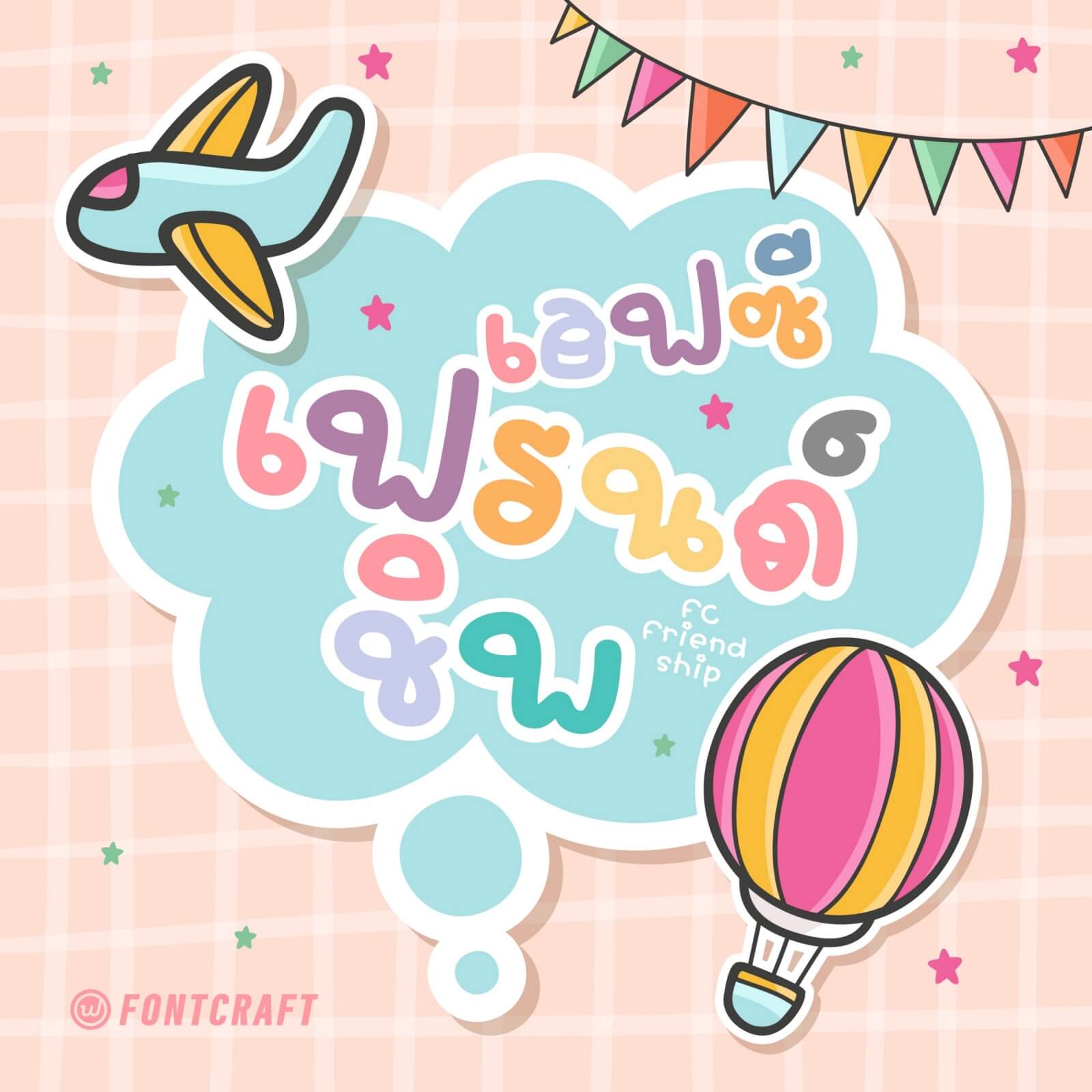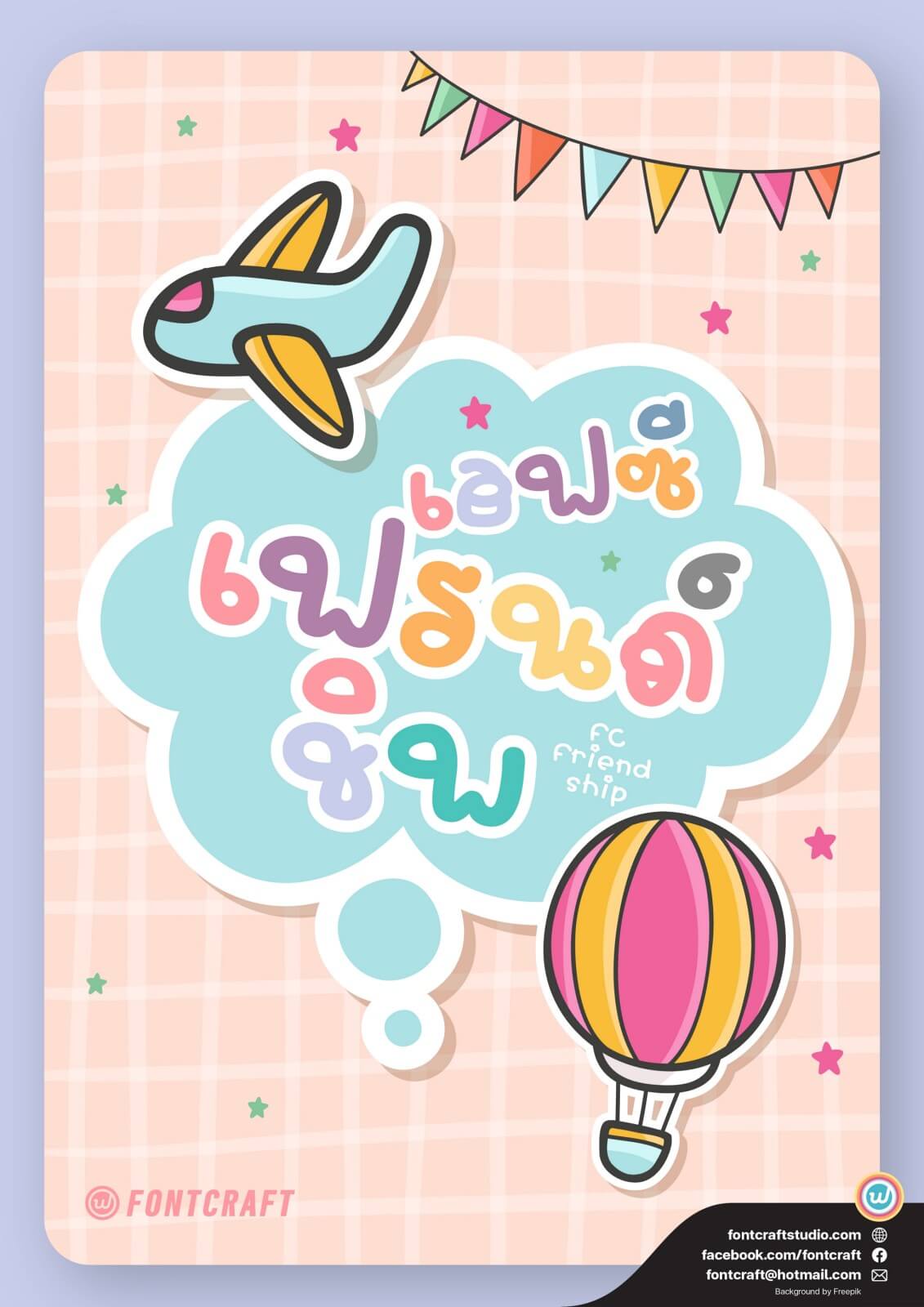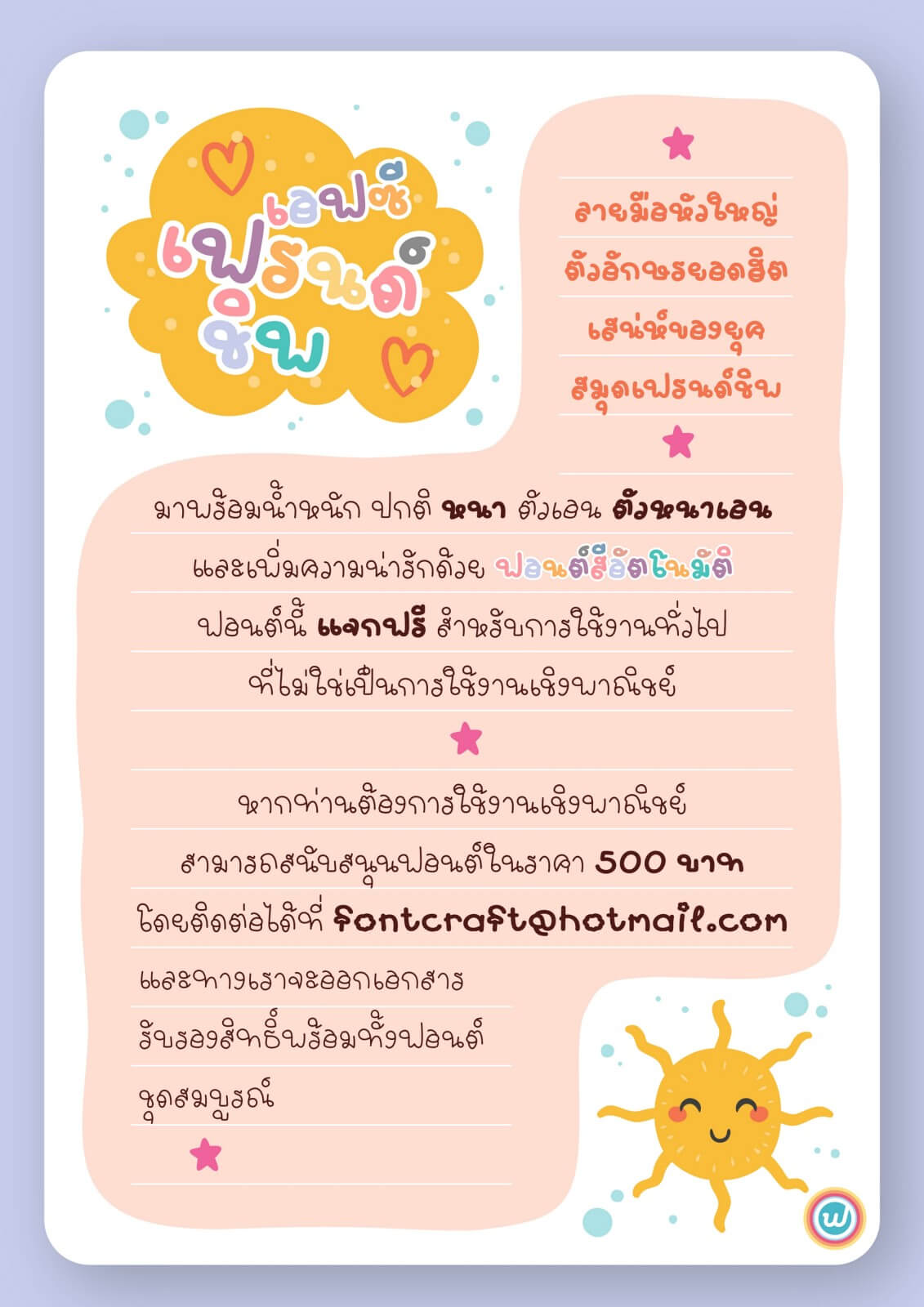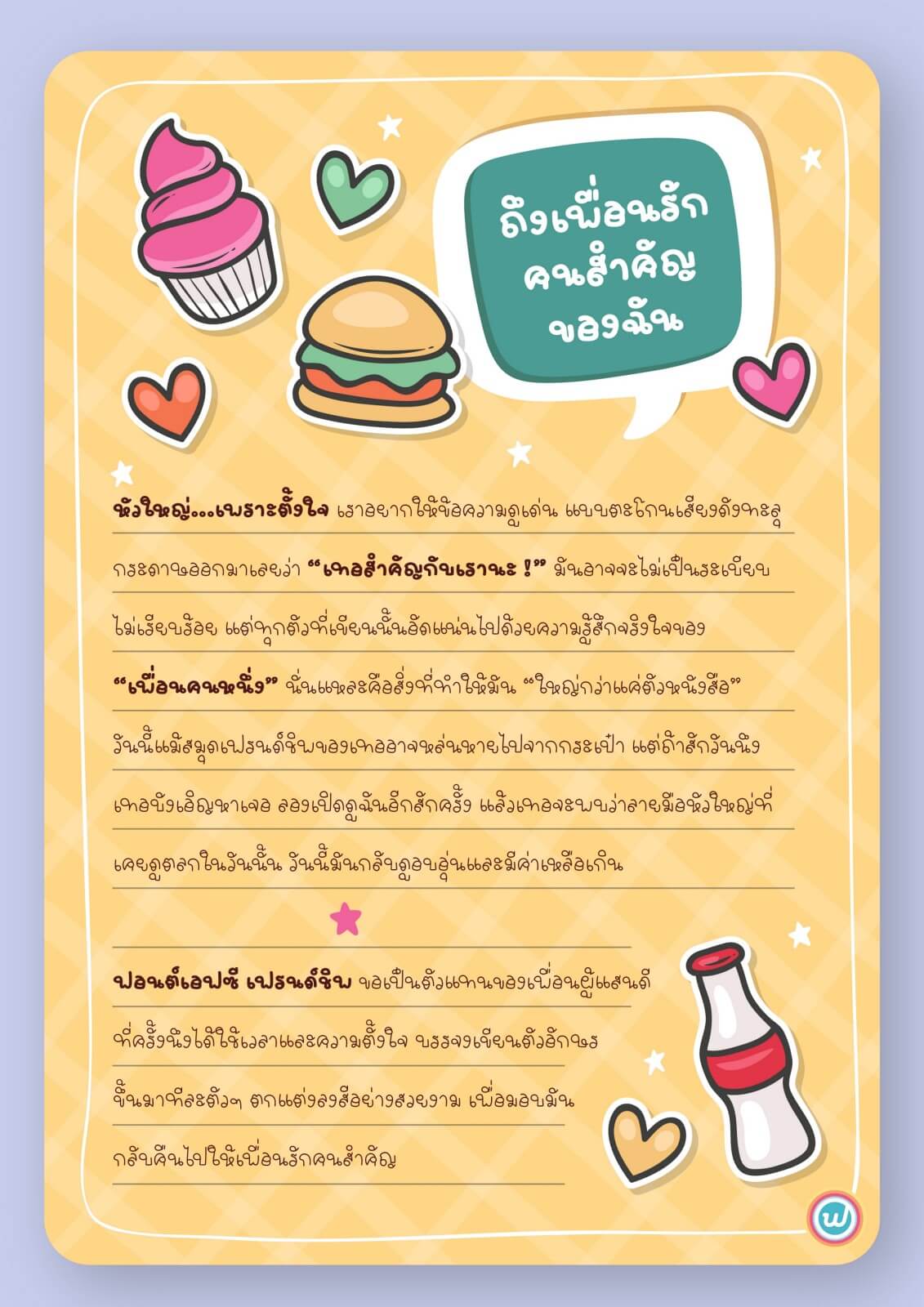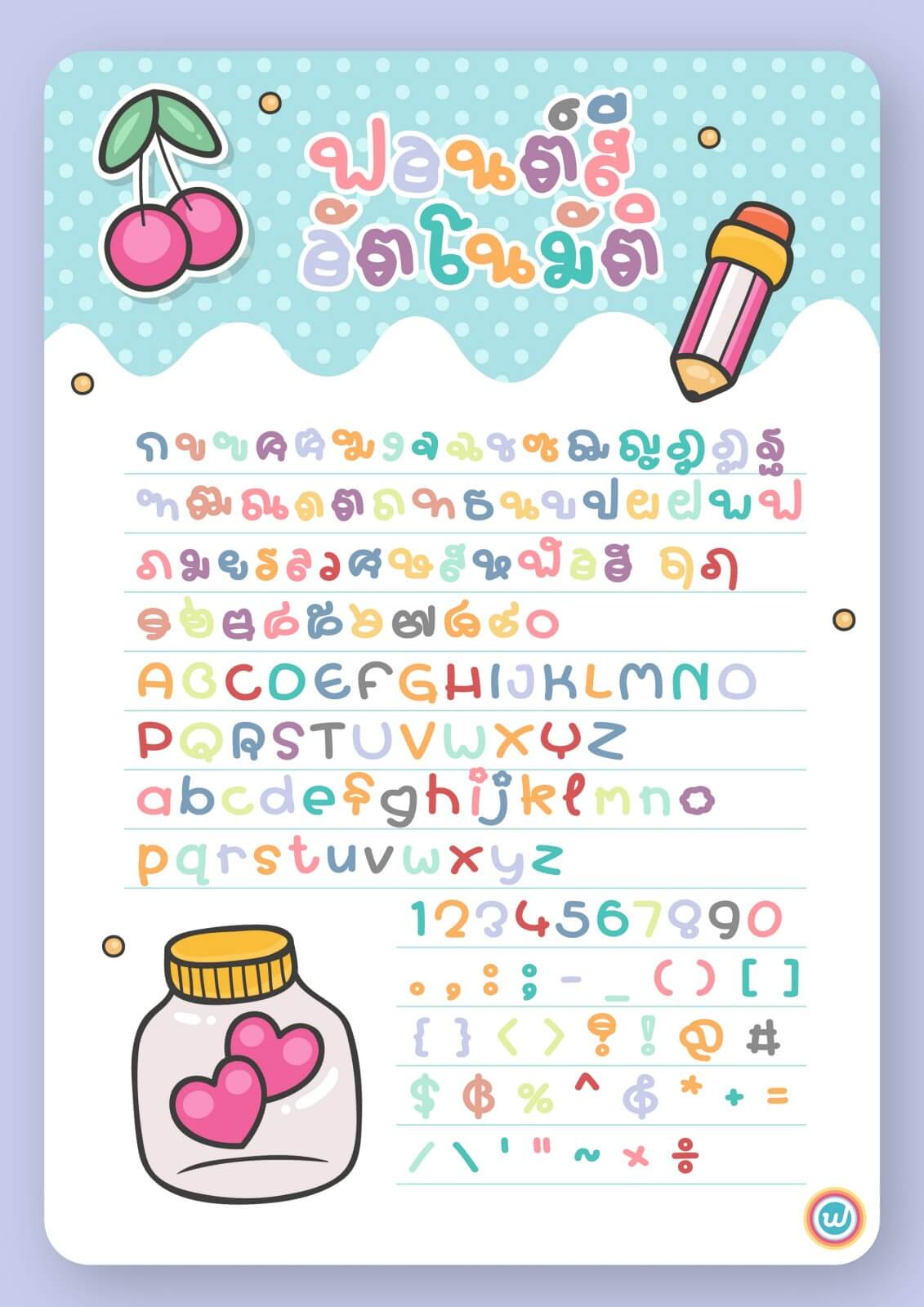
ตัวแทนของเพื่อนผู้แสนดี ที่ครั้งนึงได้ใช้เวลาและความตั้งใจ บรรจงเขียนตัวอักษรขึ้นมาทีละตัวๆ ตกแต่งลงสีอย่างสวยงาม เพื่อมอบมันกลับคืนไปให้เพื่อนรักคนสำคัญ
ฟอนต์ลายมือนี้เสมือนเป็นจดหมายเหตุลายมือไทยยุค 90 ที่ทุกคนจะตั้งใจเขียนลายมือหัวใหญ่เพื่อสื่อถึงความตั้งใจ หากเมื่อไหร่ที่คุณบังเอิญหาเฟรนด์ชิพเล่มเก่าเจอและเปิดเจอลายมือแบบนี้ ขอให้รู้ไว้นะว่าคุณน่ะเป็นเพื่อนคนสำคัญของใครสักคนที่ตั้งใจเขียนมันขึ้นมา
มาพร้อมน้ำหนักปกติ หนา ตัวเอน ตัวหนาเอน และเพิ่มความน่ารักด้วยฟอนต์สีอัตโนมัติ (Color Font)
ข้อมูลคอมพิวเตอร์ฟอนต์ : เอฟซี เฟรนด์ชิพ (FC Friendship)